双鱼座是黄道星座第十二宫,今天我来介绍关于这个星座的创意设计
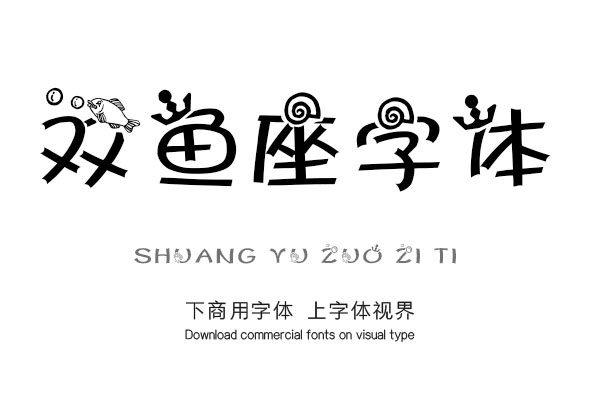
该字体线条圆润如肉嘟嘟的小手可爱至极。笔画婉转天然且不失笔法 笔画方圆并济,起收笔处为直切,更显笔画天然的张力;在字体中嵌入小鱼,泡泡等元素,使得字体更加生动有趣。
双鱼座身上有一种令人难以抵御的奇异魅力,浪漫又爱幻想,热情也很多情,性情温柔,容易相处。为黄道星座之第十二宫。